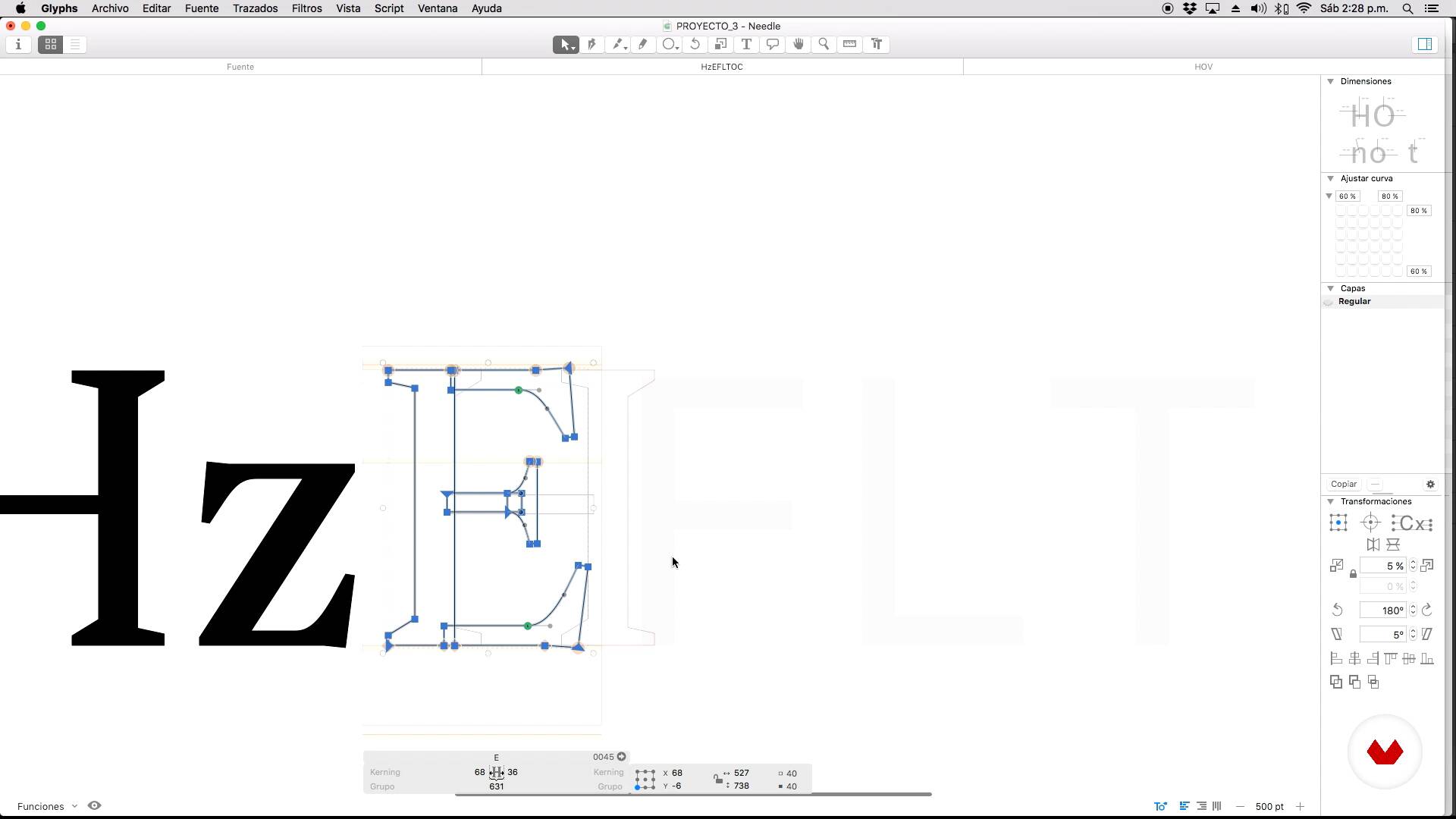
Digitale Neuinterpretation klassischer Schriftarten
High-Box-Systematisierung II
In dieser Videolektion behandelt Oscar Guerrero Cañizares das Thema: High-Box-Systematisierung II, das Teil dieses Domestika-Onlinekurses ist: Digitale Neuinterpretation klassischer Schriftarten. Lernen Sie die Methode der typografischen Wiederbelebung kennen, um alten Schriftarten ein neues digitales Leben zu verleihen.
“Was die Konstruktion des Hauptalphabets betrifft, Wir können das gesamte alphabetische System auf drei Arten erstellen: Über welche haben wir zuvor gesprochen. Diese drei Buchstaben, das H, das O und das V, Sie bieten uns die meisten zu lösenden Informationen Die meisten Buchstaben haben wir im High-Box-Alphabet. Nehmen wir das Beispiel dieser Anfangsbuchstaben. Beginnen wir mit dem Zeichnen, nachdem wir diese drei Buchstaben haben. Formen, die diesen Strukturen am ähnlichsten sind. Ich werde mit diesen vier Buchstaben beginnen: E, F, L, T, um zu sehen, wie wir speichern und verwalten könne...”